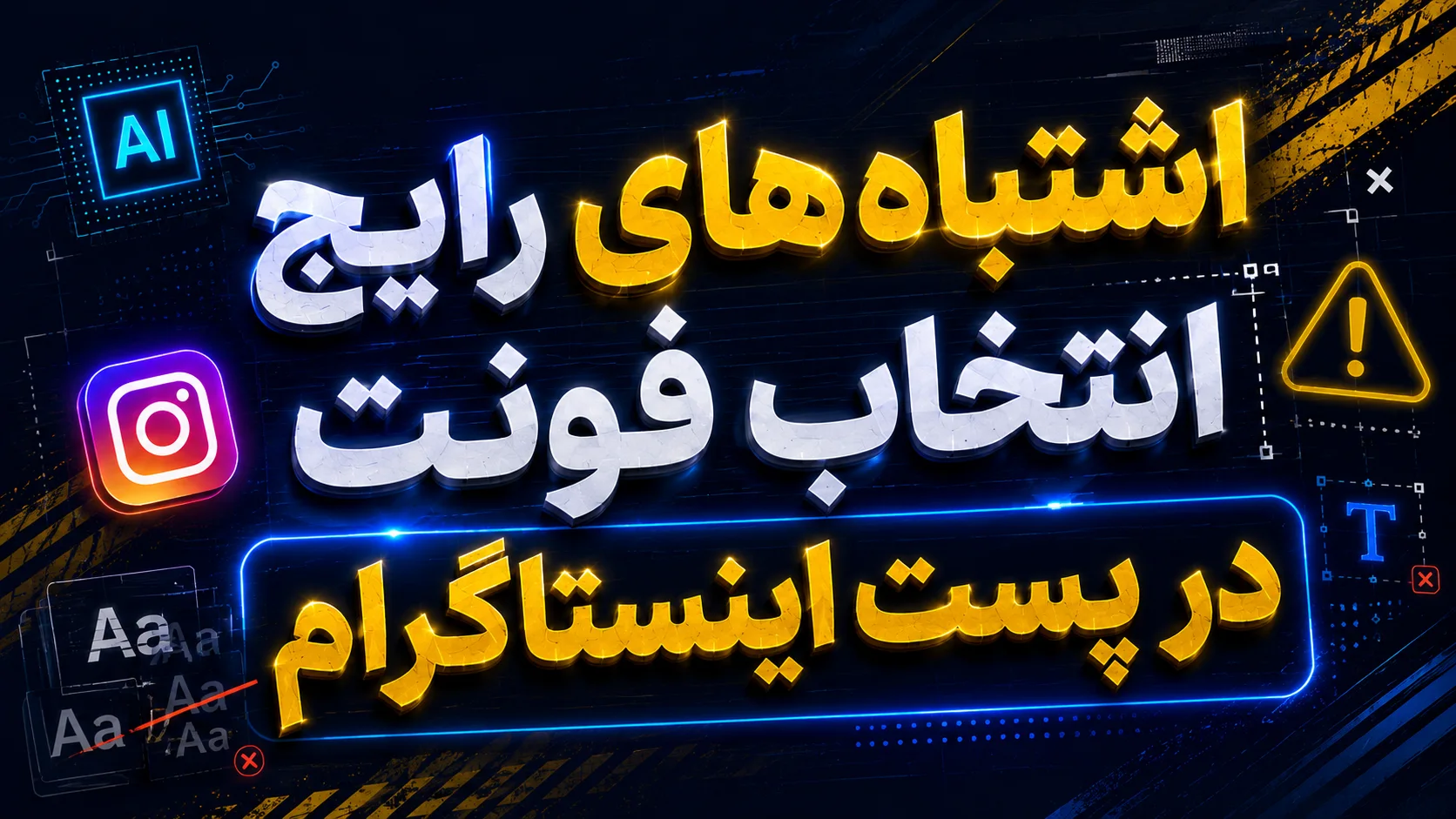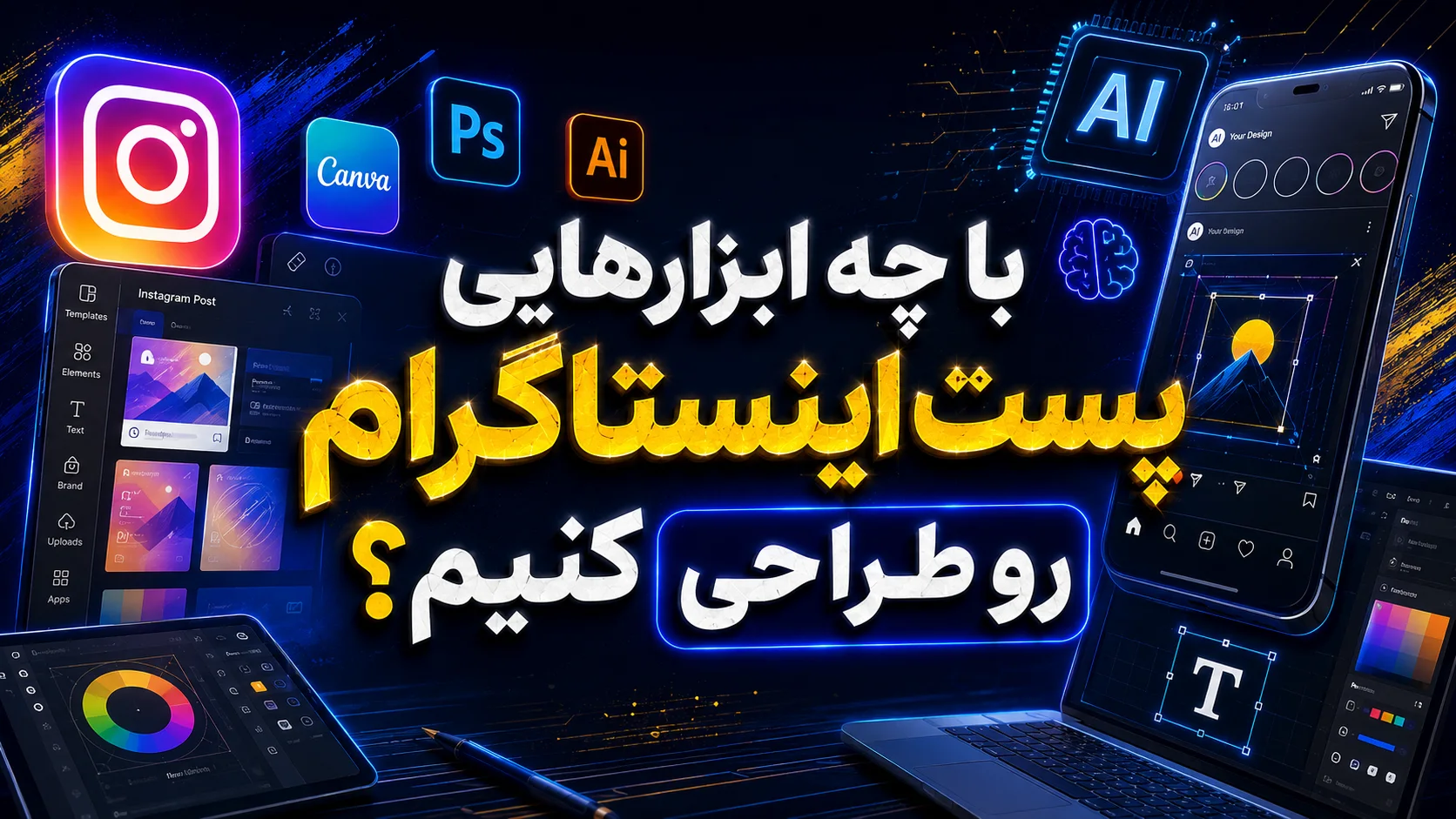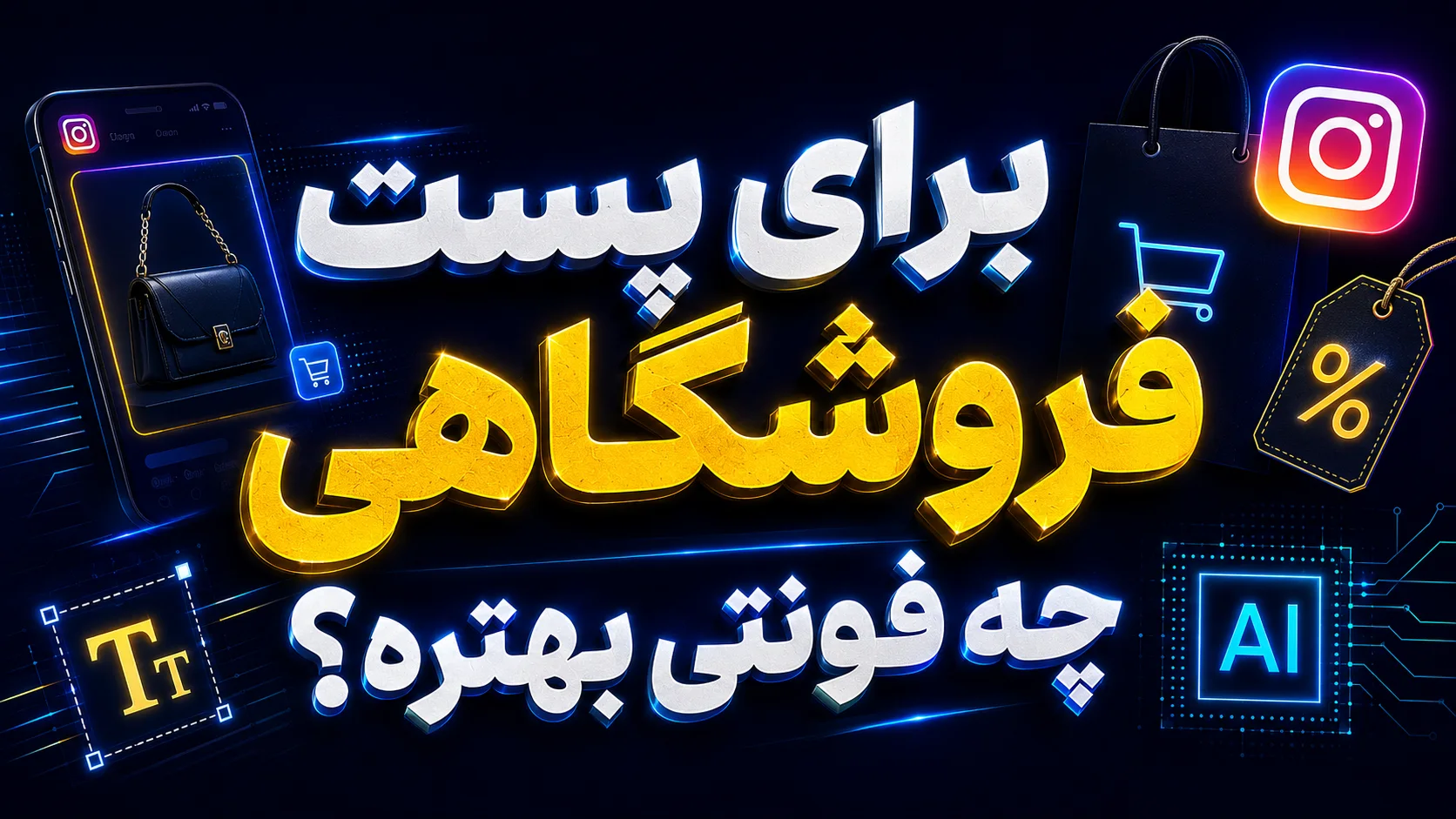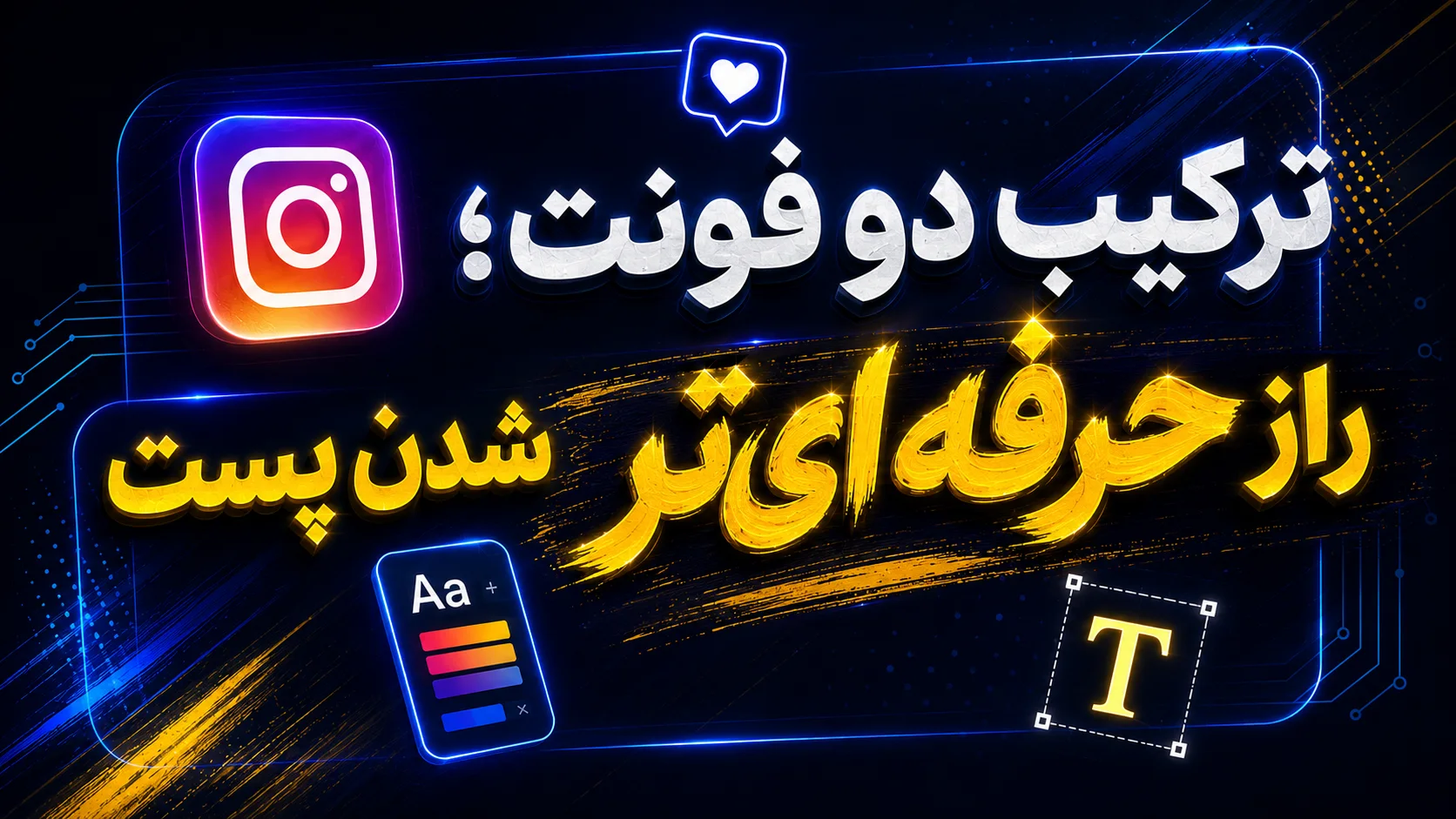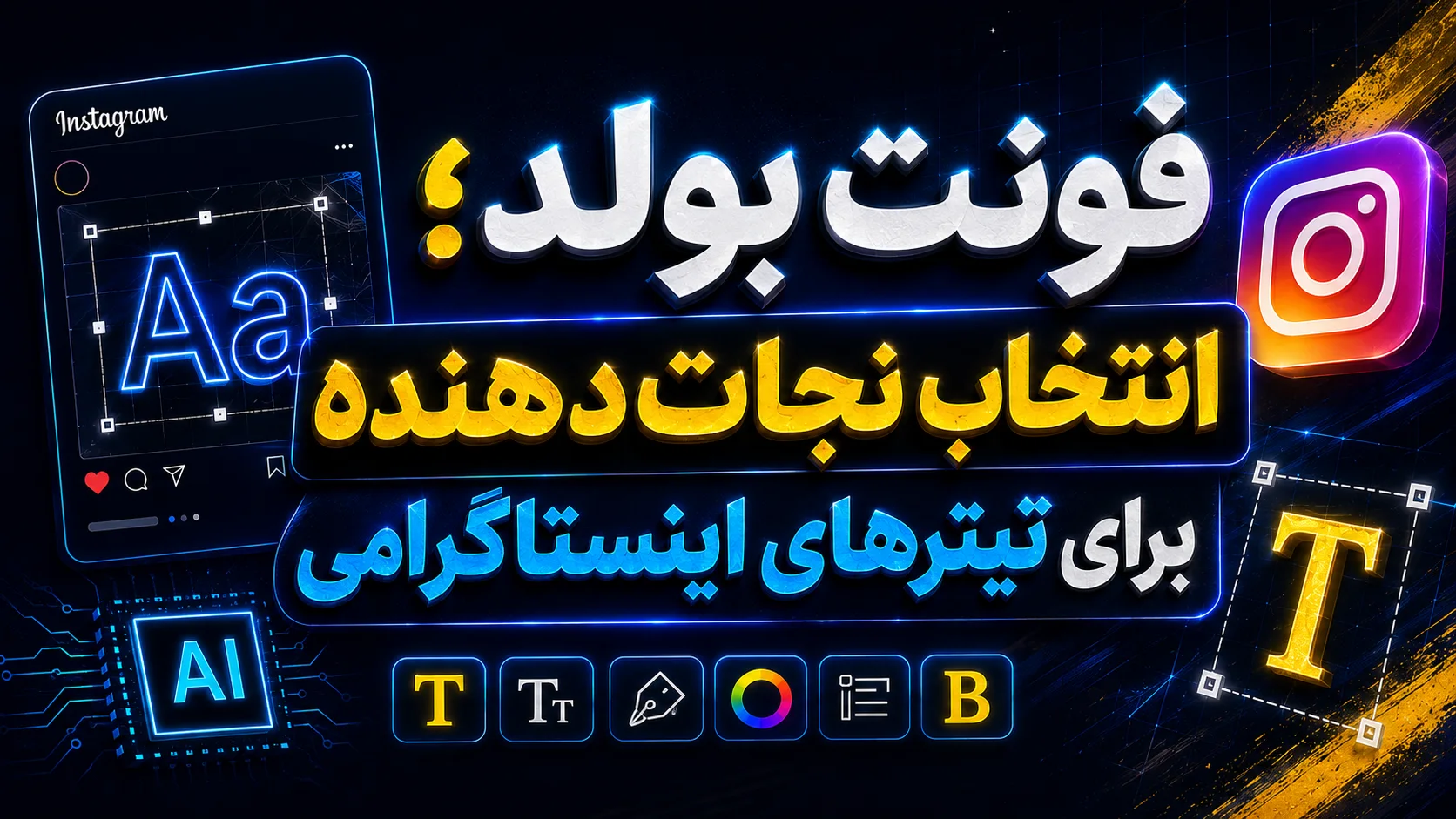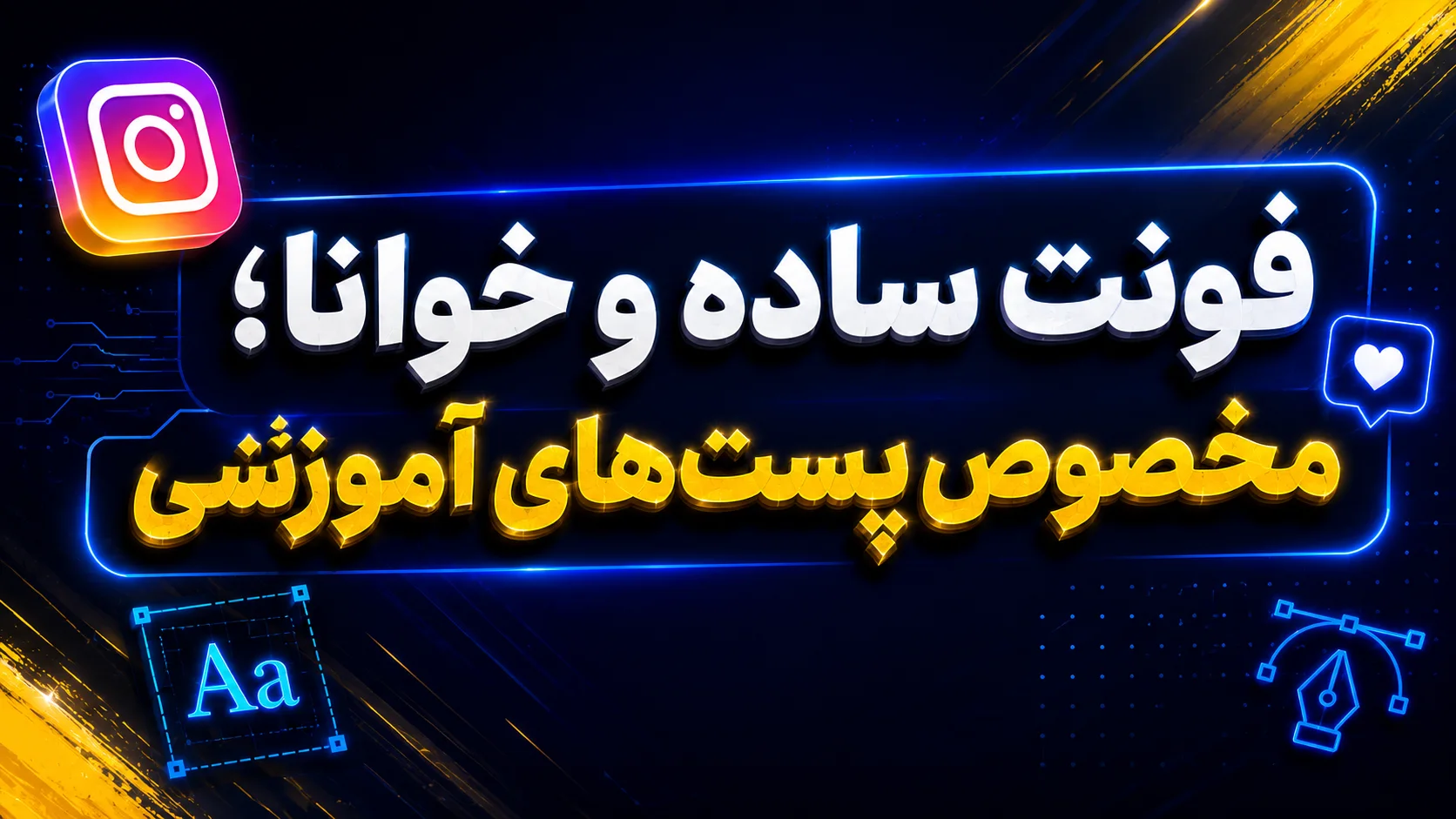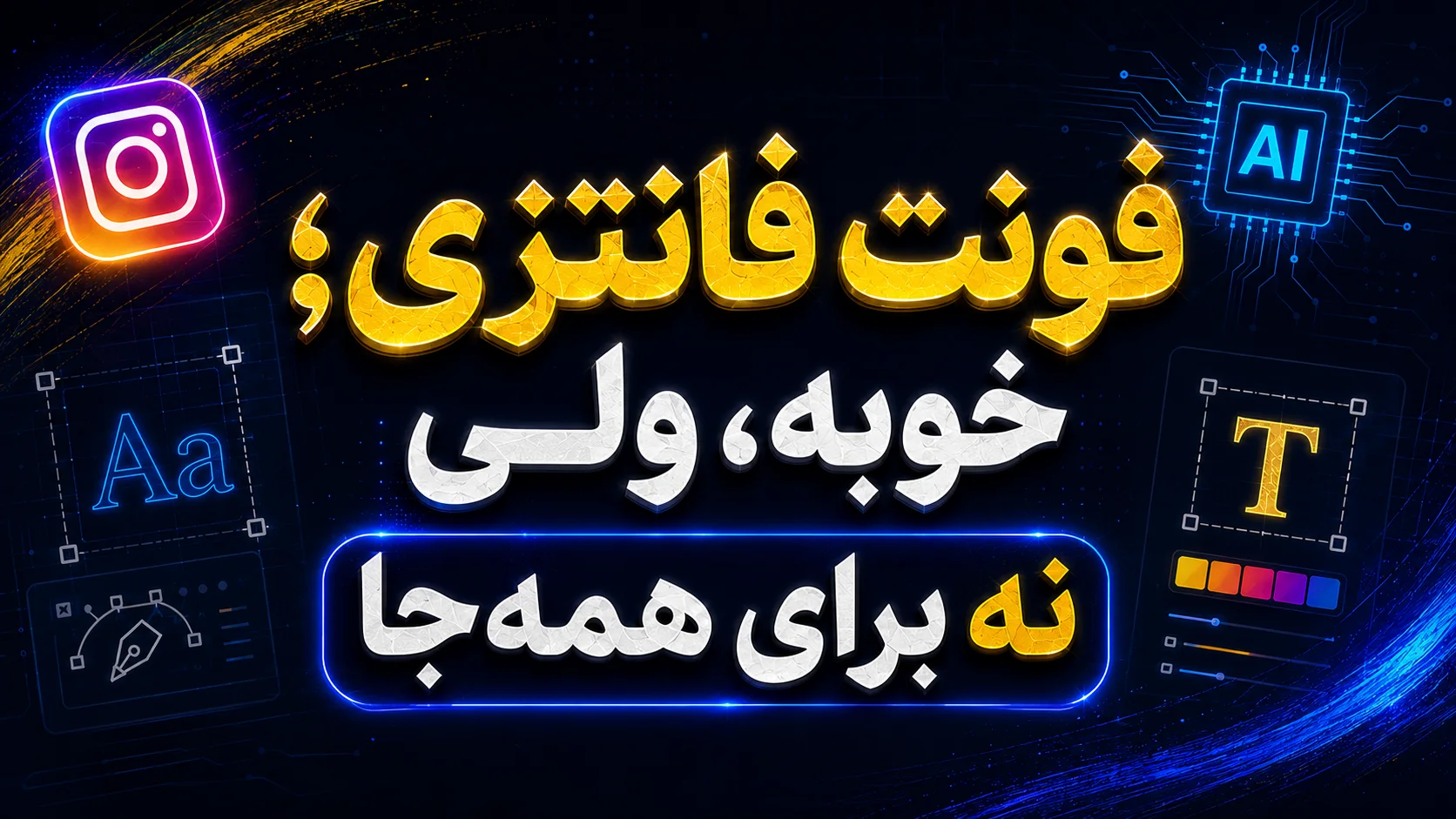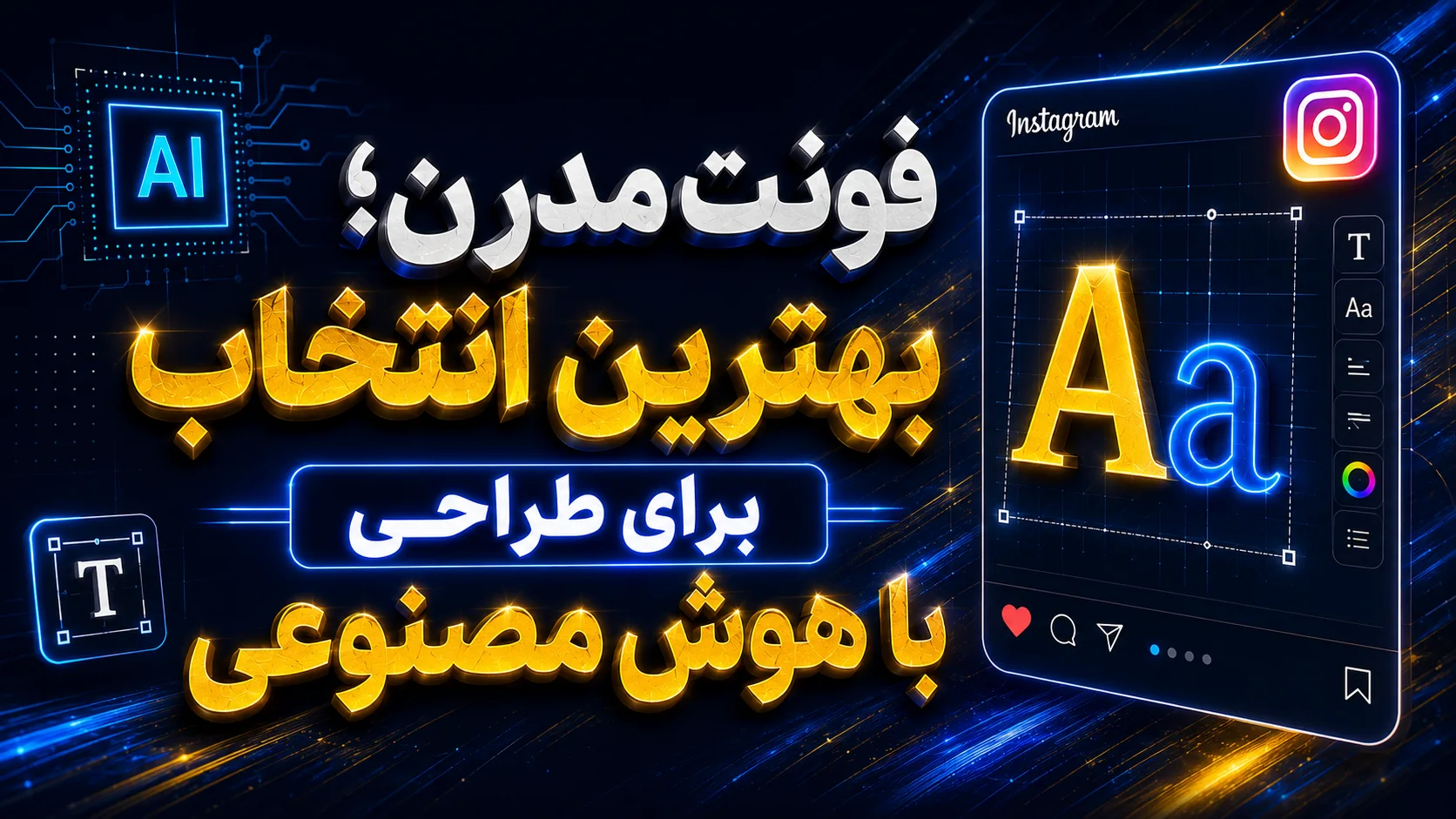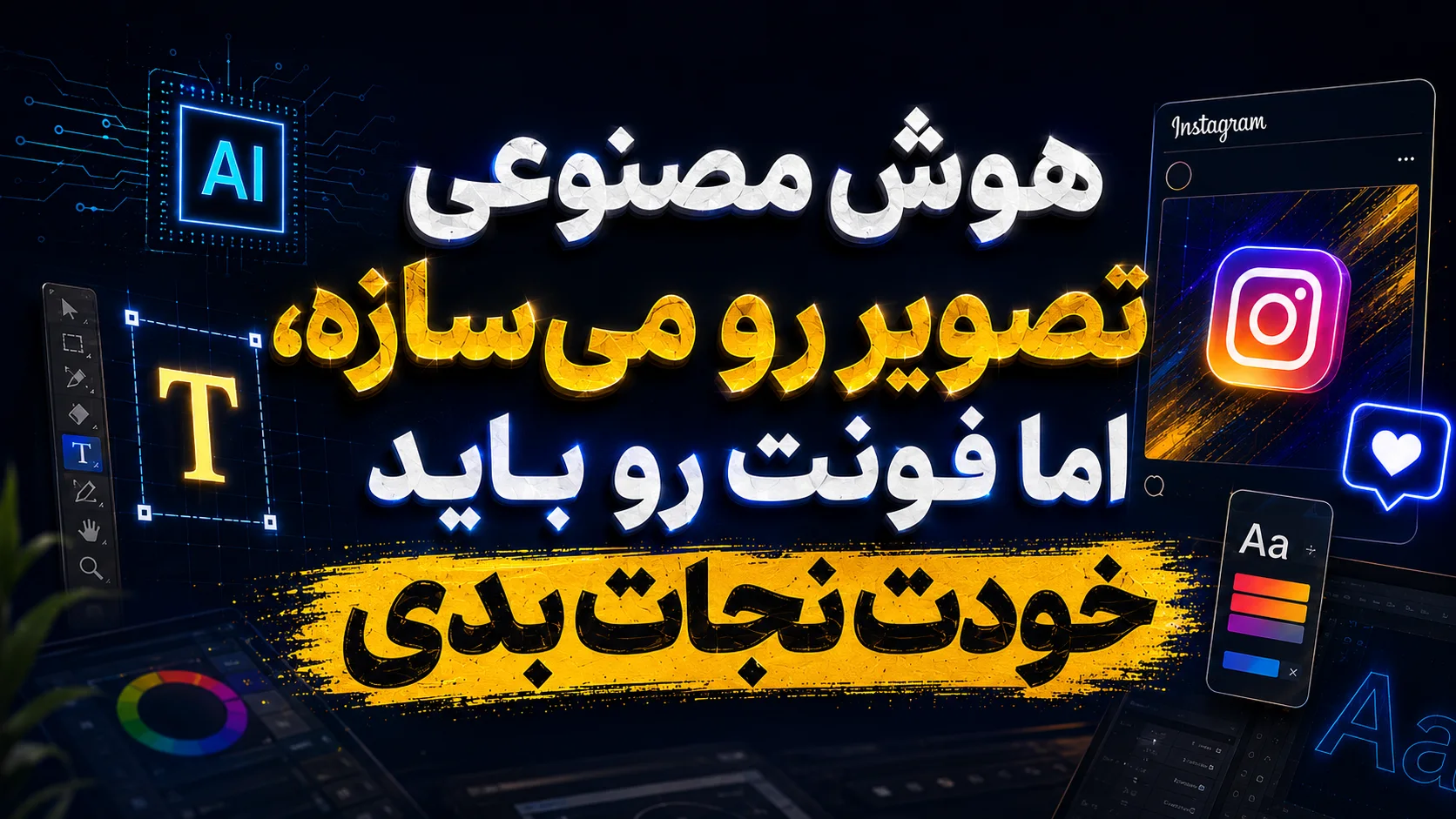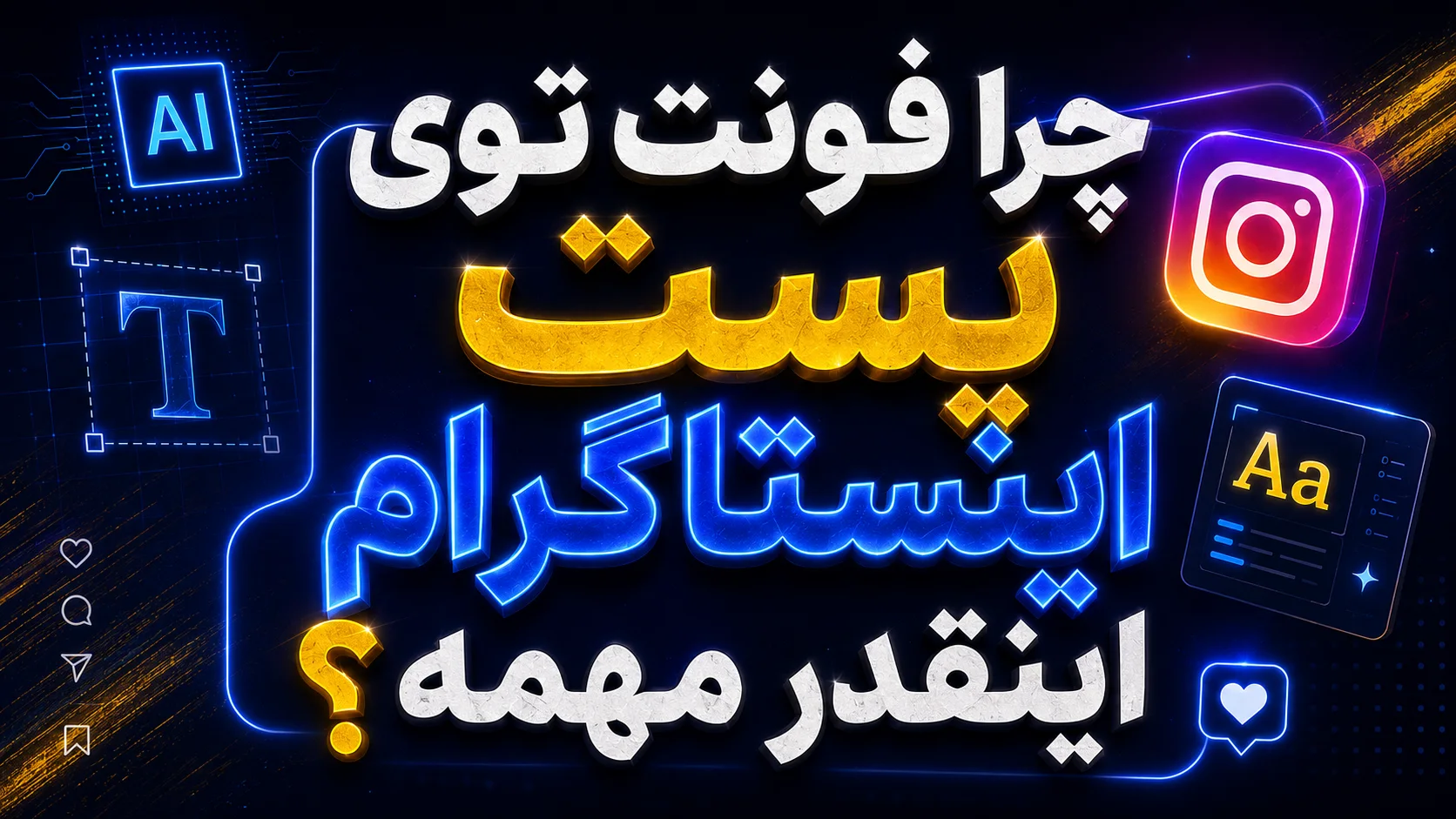
طراحی پست اینستاگرام با هوش مصنوعی؛ این فونت‌ها پستت رو نجات می‌دن!
اگه این روزا با هوش مصنوعی پست اینستاگرام طراحی می‌کنی، احتمالاً یه چیزی رو خیلی زود فهمیدی: AI می‌تونه تصویرهای خفن بسازه، ایده بده، بک‌گراند طراحی کنه، رنگ‌بندی پیشنهاد بده و حتی چندتا ترکیب جذاب جلوت بذاره؛ ولی وقتی نوبت به متن و فونت می‌رسه، همه‌چیز اون‌قدرها هم بی‌دردسر نیست.
خیلی وقتا یه پست با هوش مصنوعی می‌سازی و از نظر تصویر عالیه، ولی وقتی متن فارسی روش می‌ذاری، طرح یه‌دفعه معمولی می‌شه. چرا؟ چون فونت درست انتخاب نشده. فونت توی طراحی پست اینستاگرام فقط یه نوشته ساده نیست؛ فونت می‌تونه حس حرفه‌ای بودن، اعتماد، هیجان، فروش، آموزش یا حتی لوکس بودن رو منتقل کنه.
برای همین توی این مقاله قراره خیلی خودمونی و کاربردی بریم سراغ این موضوع که برای طراحی پست اینستاگرام با هوش مصنوعی، چه فونت‌هایی بهتر جواب می‌دن، چه مدل فونتی برای چه نوع پستی مناسبه، چه اشتباه‌هایی نباید انجام بدی و چطوری کاری کنی پستت هم دیده بشه، هم خونده بشه، هم حرفه‌ای‌تر به نظر بیاد.
چرا فونت توی پست اینستاگرام اینقدر مهمه؟
توی اینستاگرام، مخاطب خیلی سریع تصمیم می‌گیره پستت رو ببینه یا رد کنه. یعنی تو فقط چند ثانیه وقت داری توجهش رو بگیری. حالا فرض کن تصویر پستت خیلی جذابه، ولی تیترش سخت خونده می‌شه یا فونتش با موضوع نمی‌خونه. نتیجه چی می‌شه؟ مخاطب رد می‌شه و حتی فرصت نمی‌ده پیام پستت رو بفهمه.
فونت خوب باعث می‌شه پیام اصلی پست سریع‌تر دیده بشه. مخصوصاً توی پست‌های آموزشی، فروشگاهی، معرفی محصول، کاور اسلایدی و پست‌های تبلیغاتی، فونت نقش خیلی مهمی داره. چون بیشتر وقتا مخاطب اول تیتر رو می‌خونه، بعد تصمیم می‌گیره ادامه پست رو ببینه یا نه.
چرا فونت توی پست اینستاگرام اینقدر مهمه؟
هوش مصنوعی تصویر رو می‌سازه، اما فونت رو باید خودت نجات بدی
خیلی‌ها فکر می‌کنن وقتی با هوش مصنوعی طراحی می‌کنن، دیگه همه‌چیز باید از خود AI بیاد بیرون. ولی واقعیت اینه که توی طراحی فارسی، بهتره تصویر و بک‌گراند رو با هوش مصنوعی بسازی، اما متن و تایپوگرافی رو خودت جداگانه اضافه کنی.
مثلاً می‌تونی با ChatGPT یا ابزارهای تولید تصویر، برای پستت ایده بگیری. بعد با یه ابزار طراحی مثل فتوشاپ، Canva یا Adobe Express متن فارسی رو دقیق و تمیز بذاری. اینطوری هم از سرعت AI استفاده می‌کنی، هم کنترل فونت و خوانایی دست خودته.
هوش مصنوعی تصویر رو می‌سازه، اما فونت رو باید خودت نجات بدی
فونت بولد؛ انتخاب نجات‌دهنده برای تیترهای اینستاگرامی
اولین مدلی که باید جدی بگیری، فونت بولده. فونت بولد یعنی فونتی که وزن زیادی داره، سریع دیده می‌شه و برای تیتر اصلی عالیه. وقتی پست اینستاگرام طراحی می‌کنی، مخصوصاً اگه پست آموزشی، تبلیغاتی یا فروشیه، تیتر باید محکم و واضح باشه.
مثلاً تیترهایی مثل «۵ اشتباه طراحی»، «فروش ویژه»، «قبل از خرید ببین»، «این ابزار رو از دست نده» یا «پستت رو حرفه‌ای کن» با فونت‌های بولد خیلی بهتر دیده می‌شن.
اما حواست باشه فونت بولد رو برای همه متن‌ها استفاده نکنی. اگه کل پست بولد باشه، چشم مخاطب خسته می‌شه و دیگه نمی‌فهمه کدوم بخش مهم‌تره. بهترین حالت اینه که تیتر اصلی بولد باشه، زیرتیتر نیمه‌بولد و متن توضیحی ساده‌تر.
برای پست‌های اینستاگرامی، فونت‌های بولد فارسی مثل یکان‌بخ، مربع، کلمه، تیترهای ضخیم و فونت‌های مدرن سنگین می‌تونن خیلی خوب جواب بدن. البته انتخاب دقیق به سبک کارت بستگی داره. اگه پستت جدیه، فونت تمیزتر انتخاب کن. اگه تبلیغاتی و هیجانیه، فونت پرقدرت‌تر بزن.
فونت بولد؛ انتخاب نجات‌دهنده برای تیترهای اینستاگرامی
فونت ساده و خوانا؛ مخصوص پست‌های آموزشی
اگه داری پست آموزشی طراحی می‌کنی، فونت ساده و خوانا خیلی مهمه. چون مخاطب قراره متن رو بخونه، یاد بگیره و اسلایدها رو دنبال کنه. توی پست‌های آموزشی، فونت بیش از حد فانتزی یا پیچیده باعث می‌شه خوانایی کم بشه.
مثلاً برای پست‌هایی مثل «آموزش طراحی با هوش مصنوعی»، «ترفندهای فتوشاپ»، «چطور کاور بسازیم؟» یا «راهنمای انتخاب فونت»، بهتره از فونت‌های ساده و مرتب استفاده کنی. این مدل فونت‌ها شاید خیلی جیغ و هیجانی نباشن، ولی باعث می‌شن مخاطب راحت‌تر با محتوا ارتباط بگیره.
اینجا یه نکته مهم وجود داره: پست آموزشی باید قابل ذخیره شدن باشه. یعنی مخاطب وقتی می‌بینه متن‌ها تمیز و واضح‌ان، احتمال اینکه پست رو سیو کنه بیشتر می‌شه. پس طراحی آموزشی فقط قشنگ بودن نیست؛ باید کاربردی و قابل خواندن هم باشه.
فونت ساده و خوانا؛ مخصوص پست‌های آموزشی
فونت فانتزی؛ خوبه، ولی نه برای همه‌جا
فونت فانتزی می‌تونه یه پست رو خاص‌تر کنه، اما اگه اشتباه استفاده بشه، خیلی سریع طرح رو آماتور نشون می‌ده. مشکل فونت‌های فانتزی اینه که همیشه خوانا نیستن. مخصوصاً وقتی متن طولانی باشه یا اندازه فونت کوچیک بشه، مخاطب سخت می‌خونه.